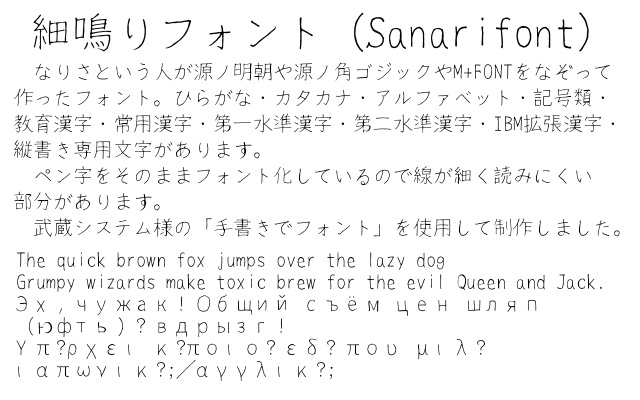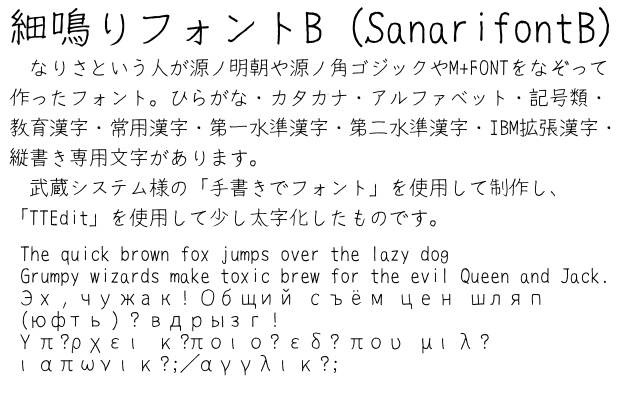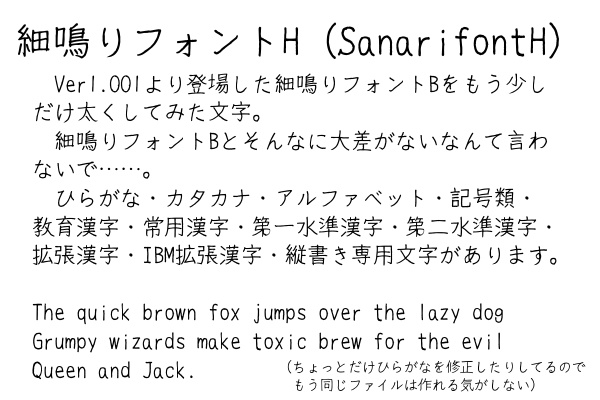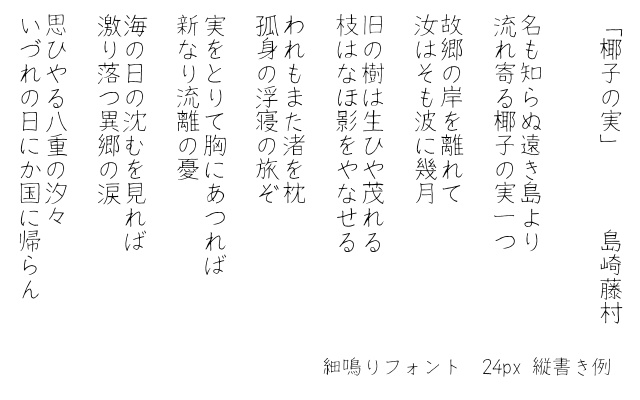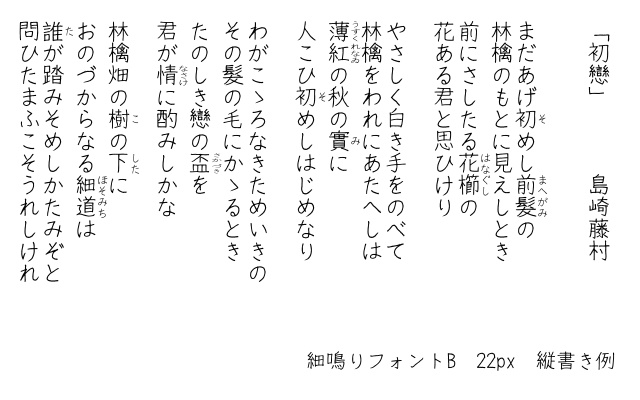
細鳴りフォント
細鳴りフォント ペン字そのままフォント化したもの。線が細いので視認しづらい部分があると思います。固定幅。 細鳴りフォントB 細鳴りフォントを太字化したもの。こちらのほうが視認性があるので使いやすいと思います。固定幅。 細鳴りフォントH(Ver1.001より) 細鳴りフォントをBよりももう少しだけ太字化したもの。固定幅。 収録文字 ひらがな・カタカナ・アルファベット・記号類・教育漢字・常用漢字・第一水準漢字・第二水準漢字・拡張漢字・IBM拡張漢字・縦書き専用文字・ギリシア文字・ロシア文字 印刷用に作ったので、web表示はあまり向いていません。 画像解像度300dpi以上での使用だと文字が見やすくなるかもしれません。
名前の由来みたいなことを。
手書きの際にお借りした「源ノ角ゴジック」や「源ノ明朝」のような日本風の名前を考えていた時に、自分のハンドルネームをちょっと変えたものを入れてみたところ さなり【細鳴り】 小さな物音。 「歩ありくといへども、-もなく、忍び歩ありきのてい也/御伽草子・猫」 ――大辞林 第三版の解説より という言葉を見つけ、おおっぴらには使えないけれど小さなことには使えるフォントになってほしいなという気持ちと、日本の言葉を使ってフォント名をつけるにはとてもいいんじゃないだろうか、ということでつけてみました。